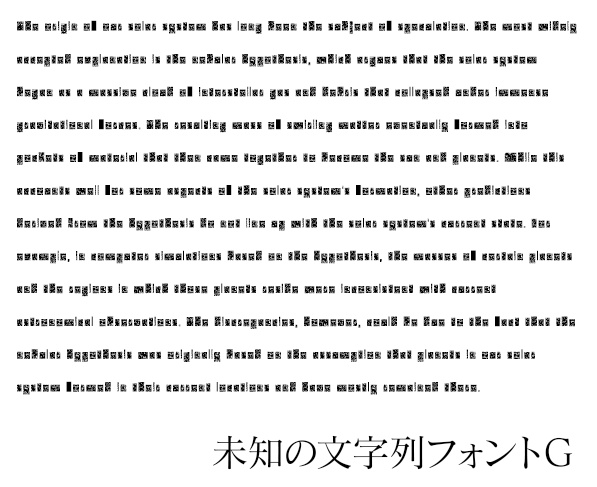
未知の文字列フォント Unknown-font
宇宙語や魔法言語、古代語とかなんかそういう「未知の言語」を表現したいときの手書きの手間を省くフォントです。 ※アルファベットに対応しています。数字は非対応です。 ※同人・商用フリーです。クレジットはご自由にどうぞ ※再配布だけは不可です。 This font saves you the trouble of handwriting when you want to express 'unknown languages' such as space languages, magical languages, ancient languages or the like. Alphabets are supported. Numbers are not supported. Free for social and commercial use. Feel free to give credit where credit is due. Redistribution only is not allowed.